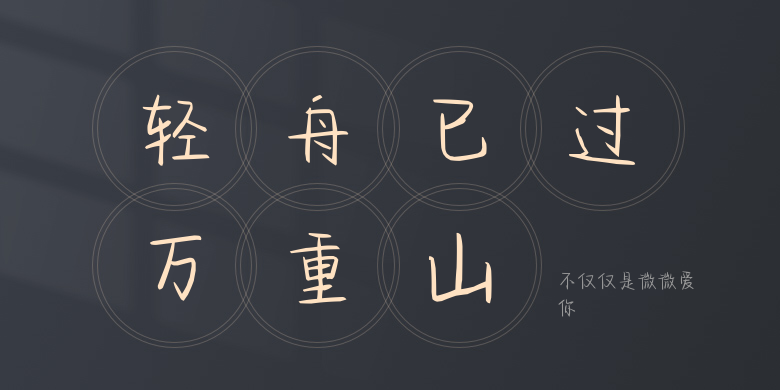
不仅仅是微微爱你
不仅仅是微微爱你,这款字体结构工整、笔画清晰,兼顾美观与易读性,适用于标题、正文、海报、包装、LOGO 等多种场景。字形优雅稳定,风格百搭耐看,适配日常排版与创意设计,让文字呈现更舒适、更具质感。不仅仅是微微爱你一笔一画,皆是细节,以均衡的比例、流畅的线条打造舒适视觉体验,字形端正大气,风格简约现代。无论是商业设计、品牌宣传还是日常排版,都能轻松驾驭,让文字更有格调与力量。不仅仅是微微爱你字体下载。